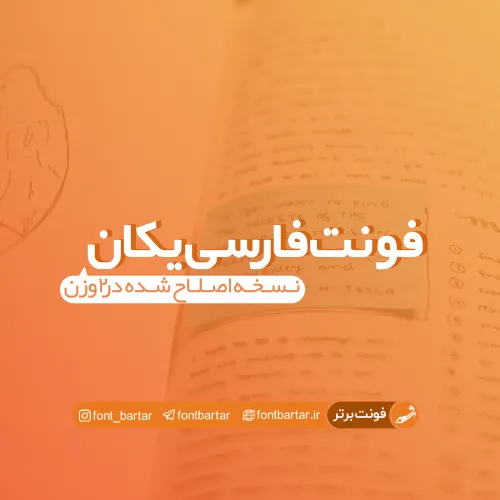
فونت یکان پلاس
فونت فارسی یکان پلاس YekanPlus font یک فونت با ساختاری منظم می باشد، این فونت با سبک خاص خود می تواند جلوه زیبایی به طرح های شما بدهد.
فونت یکان پلاس مورد استفاده برای:
• طراحان وب سایت و گرافیست های خلاق می توانند از این فونت زیبا فونت در طراحی پروژه های تبلیغاتی و تجاری خود کمک بگیرند.